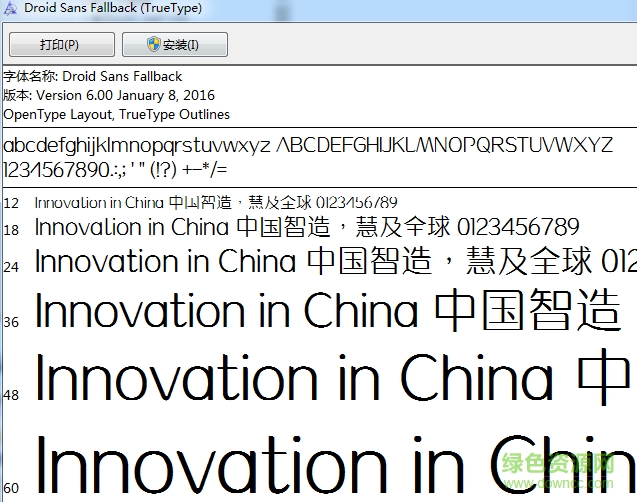
水云細(xì)水流字體是一款個(gè)性中文字體,字體非常纖細(xì)柔和,字體給人非常寧靜安逸的感覺,有喜歡的朋友可以來綠色資源網(wǎng)免費(fèi)下載使用!
水云細(xì)水流字體非常柔美,讓人看見這一字體就已經(jīng)沉浸其中了,感受字體的美,如果您需要的話,就趕快來綠色資源網(wǎng)下載吧!